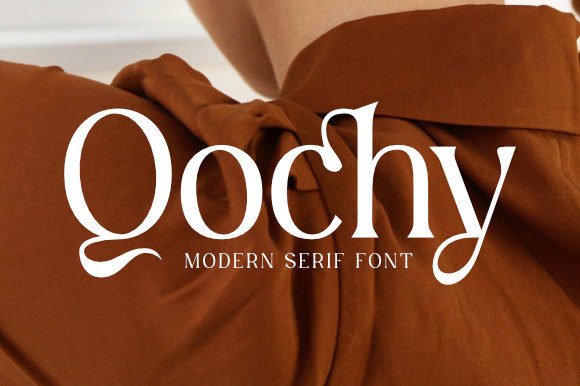
[Creativefabrica] Qochy Font (2021)
Qochy - это простой, элегантный и адаптируемый шрифт с засечками.
Не слишком тонкий и не слишком толстый, сбалансированный и разнообразный, этот шрифт был создан для того, чтобы подчеркнуть красоту ваших проектов.